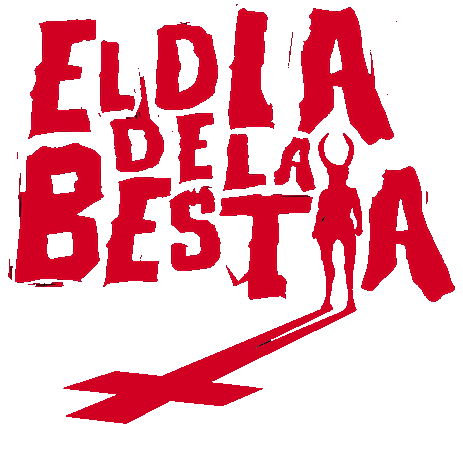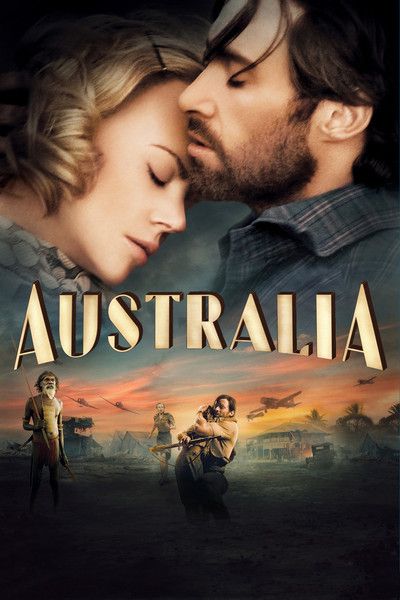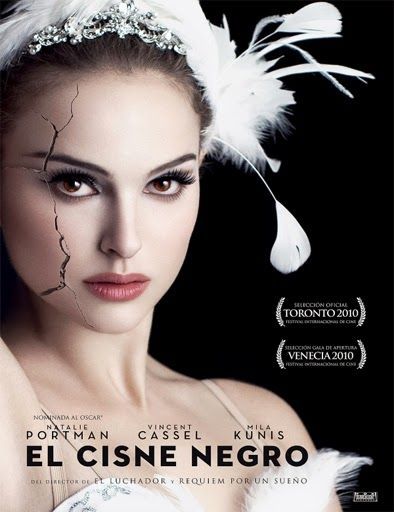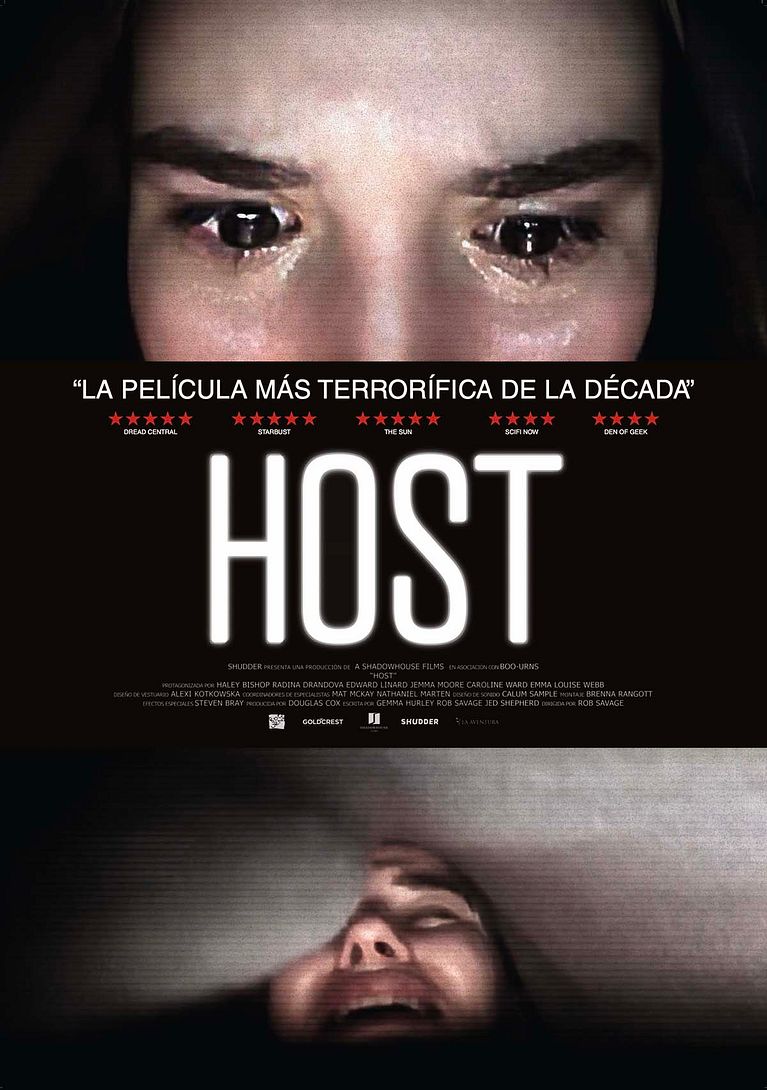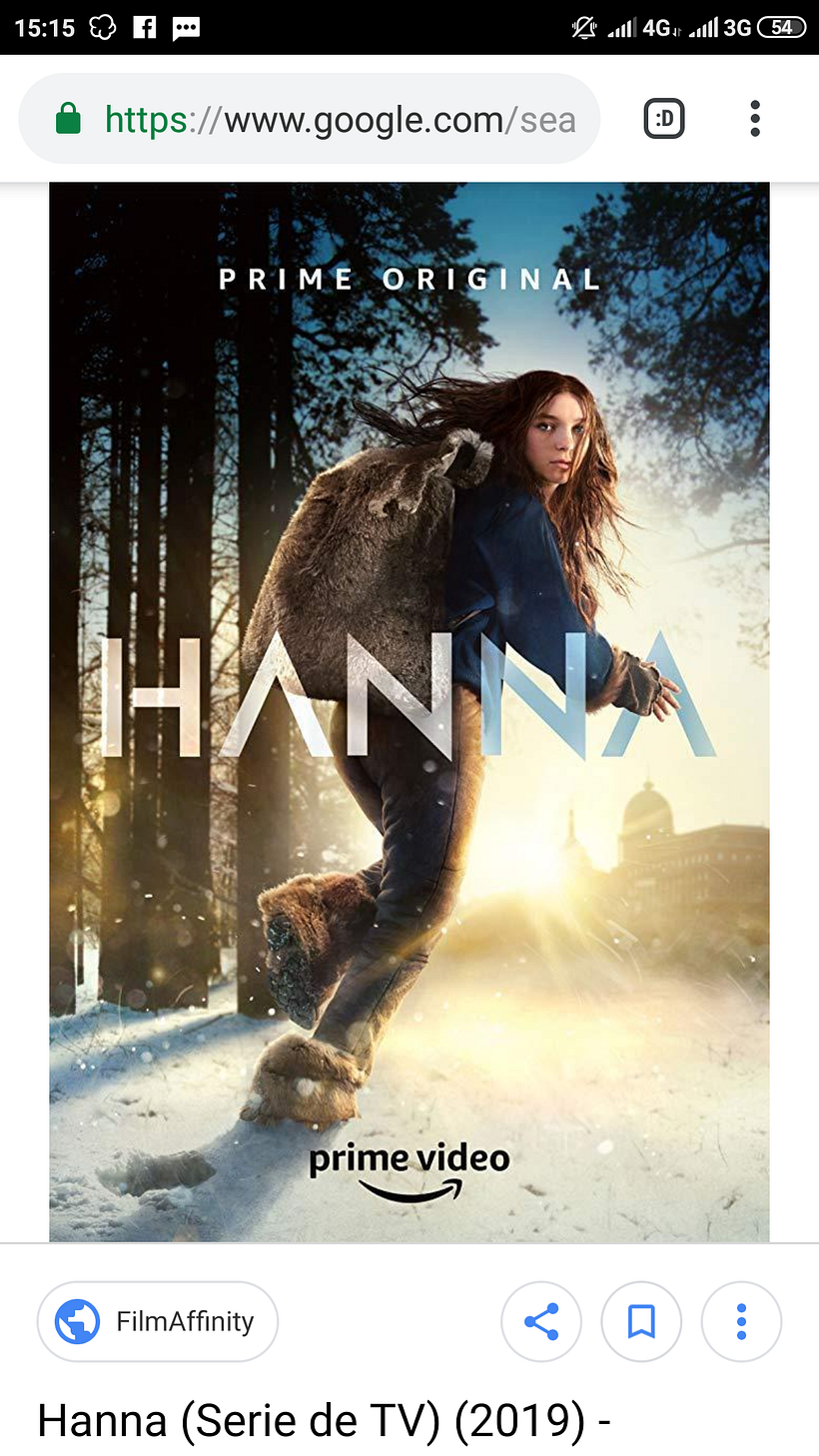
Tipografías usadas en carteles de películas
Me he dado cuenta de que en muchisimos carteles, sobre todo americanas, se usa una mismo tipo para los creditos de la parte inferior, productoras, colaboraciones, etc, etc. Es muy alta y condensada no se si se tratará de alguna helvetica "retocada" o si se trata de una tipo que es asi originalmente. Si alguien sabe algo, os agradeceria que lo comentaseis, muchas gracias.
Os dejo un ejemplo de cartel donde aparece la tipo a la que me refiero
Alguien me puede decir que tipo de tipografía es usada en la película de host (2020)
La del titulo principal es muy parecida a Futura pero creo que no es exactamente esa
Alguien sabe que tipografías se usan en este afiche de la pelicula del cisne negro
creo que son 4 tipografias distintas.
Hola! Alguien sabría decirme que tipografía es la usada en este título, gracias.
Buenas, soy nuevo por aqui y tengo una mega duda, porque hace tiempo existia una fuente concreta que se uso (o al reves) para "El dia d ela bestia" y ahora aparte de haberla perdido, no la encuentro...
Hola !! Alguien sabe cuál es la tipografía de Hanna , la serie ??? Se estrena este año! Gracias !!
La que buscas es la Univers Ultra Condensed:
Yo una vez tuve que diseñar un ficticio de un cartel de película y para falsear los créditos utilicé esta tipo.
Esta otra te "regala" a modo de dingbats los títulos ya diseñados y maquetados, pero sólo en la lengua de Shakespeare. :(